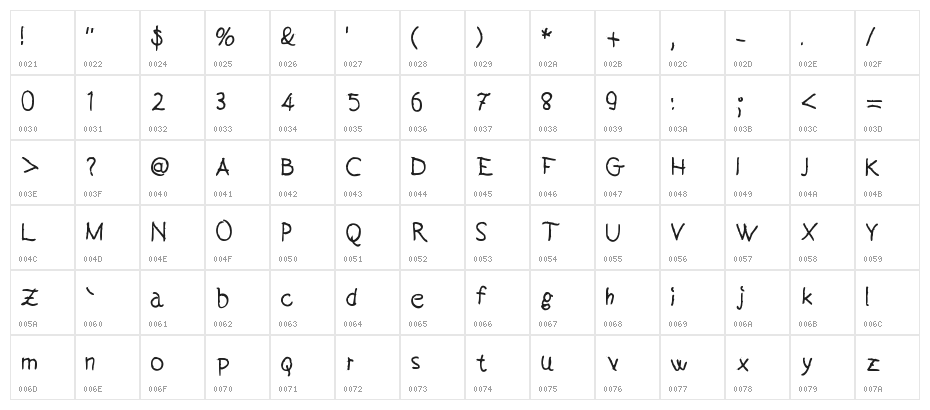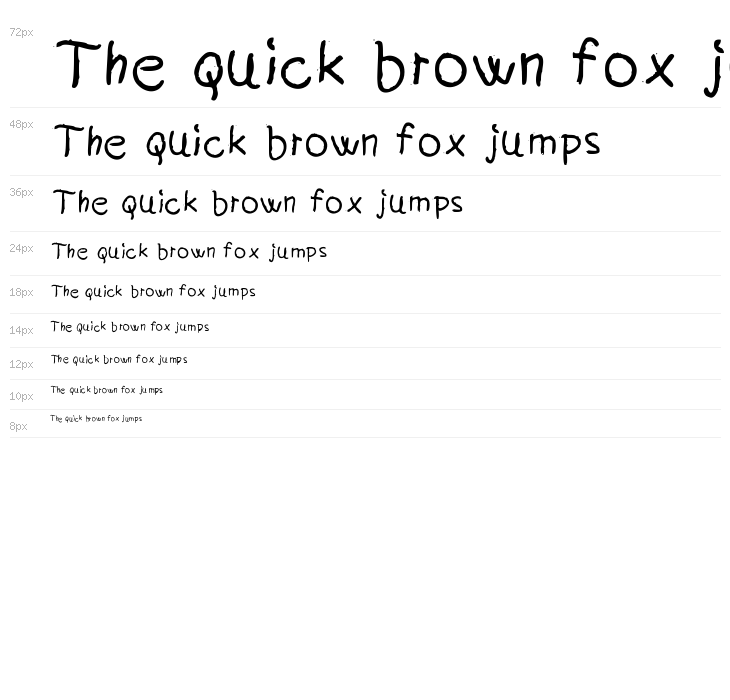
Handeer Medium Font
| 全体的なスタイル | Casual, Artistic |
| 用途 | Headlines, Artistic projects, Personal branding |
| おすすめプロジェクト | Ideal for creative projects such as greeting cards, invitations, personal branding, and artistic posters. |